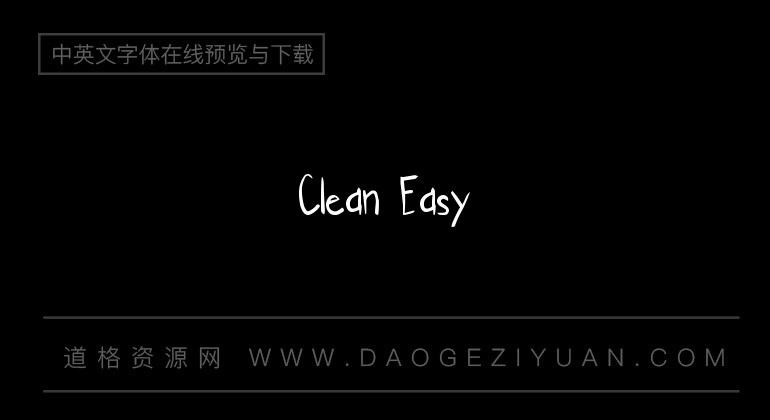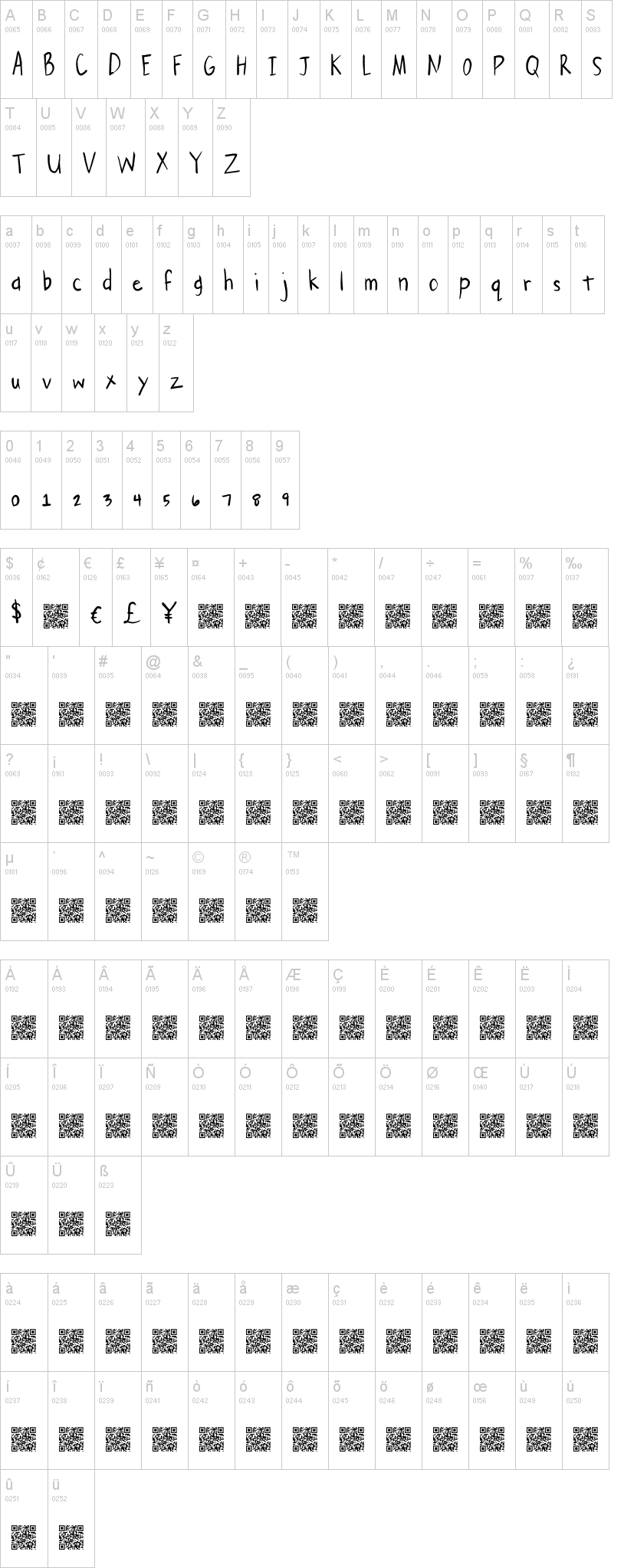
Clean Easy
Clean Easy 是一款简洁易读的字体,由设计师 Rian Hughes 创作。它的特点是字母的线条清晰流畅,间距适中,字母形态整齐,易于阅读和识别。 Clean Easy 字体家族包括 Regular、Italic、Bold 和 Bold Italic 四种字体样式,适用于不同的设计项目和排版需求。这款字体适合用于印刷品、海报、标识、网站等各种设计场景。
Clean Easy是一款非常不错的手写艺术字体,具有很好的视觉感,适合于文化类的宣传设计、商业类品牌的广告和产品包装设计以及个性化文字排版等较多场景。